Einen Namen tippen, einen Stil wählen, ein PNG herunterladen. Das ist alles, und es dauert etwa zehn Sekunden.
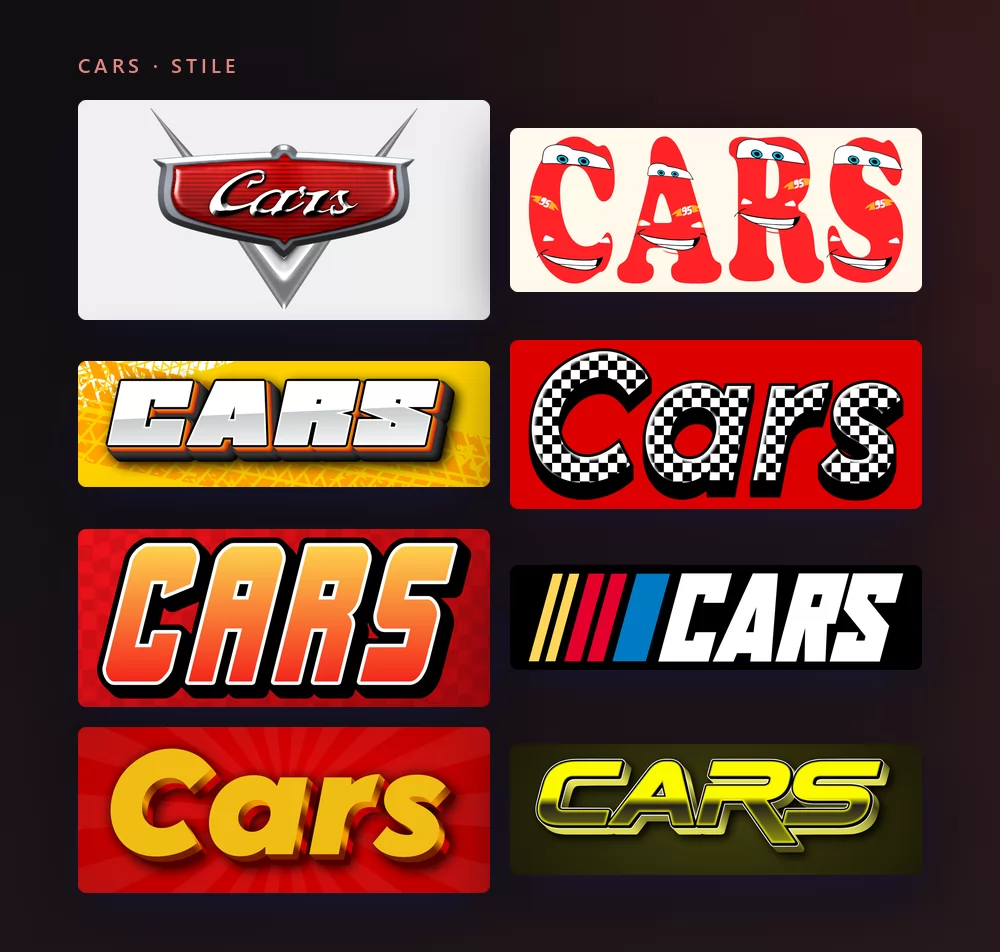
Alle stammen aus demselben Cars-Schriftgenerator, nur mit einem anderen Stil aus der Liste. Nichts zu installieren, kein Konto, und alle Stile oben sind kostenlos.
Über die Cars-Schrift
Cars ist ein Pixar-Film von 2006, eine Komödie in einer Welt, in der die Autos die Figuren sind. Sein Titel ist nicht getippt, er ist gebaut: eine Chromschrift in einem Wappenschild, näher am Ornament auf der Motorhaube einer Limousine der fünfziger Jahre als an einem Filmplakat.
Das Lettering selbst kommt Magneto Bold sehr nahe, gezeichnet von Leslie Cabarga und 1995 bei Font Bureau erschienen. Microsofts eigene Typografie-Seite beschreibt sie als Erinnerung an "die Chromleisten-Schriftzüge auf den runden Formen von Kühlschranktüren und Kofferraumdeckeln der vierziger und fünfziger Jahre", also genau die Epoche, die der Film zitiert.
Und hier ist, was jede Download-Seite auslässt. Magneto ist eine kommerzielle Schrift, und der übliche Rat lautet, sie zu kaufen. Aber Microsoft führt sie unter den Schriften, die es ausliefert, Datei Magnetob.ttf, und schreibt, dass sie in den Office-Anwendungen verfügbar ist. Wenn du Microsoft Office auf dem Rechner hast, hast du Magneto Bold sehr wahrscheinlich längst installiert.
Cars-Text erstellen
Schritt 1. Den Namen tippen
Öffne den Generator und ersetze den Beispieltext durch deinen. Das Emblem wird um das Wort herum gebaut, es ist also für einen Vornamen gemacht: das Schild füllt sich, während du tippst.
Schritt 2. Einen Stil wählen
Der Stil auf der Zielseite ist das Emblem: Chromschrift, roter Lack, silbernes Schild. In der Liste steht auch die ganze Rennseite des Films, Zielflaggen, Reifenspuren, Rennstreifen und die Buchstaben mit den Augen von Lightning McQueen. Im Reiter "Stil" lassen sich Füllung, Kontur und Schatten bei beiden ändern.
Schritt 3. Das Format wählen
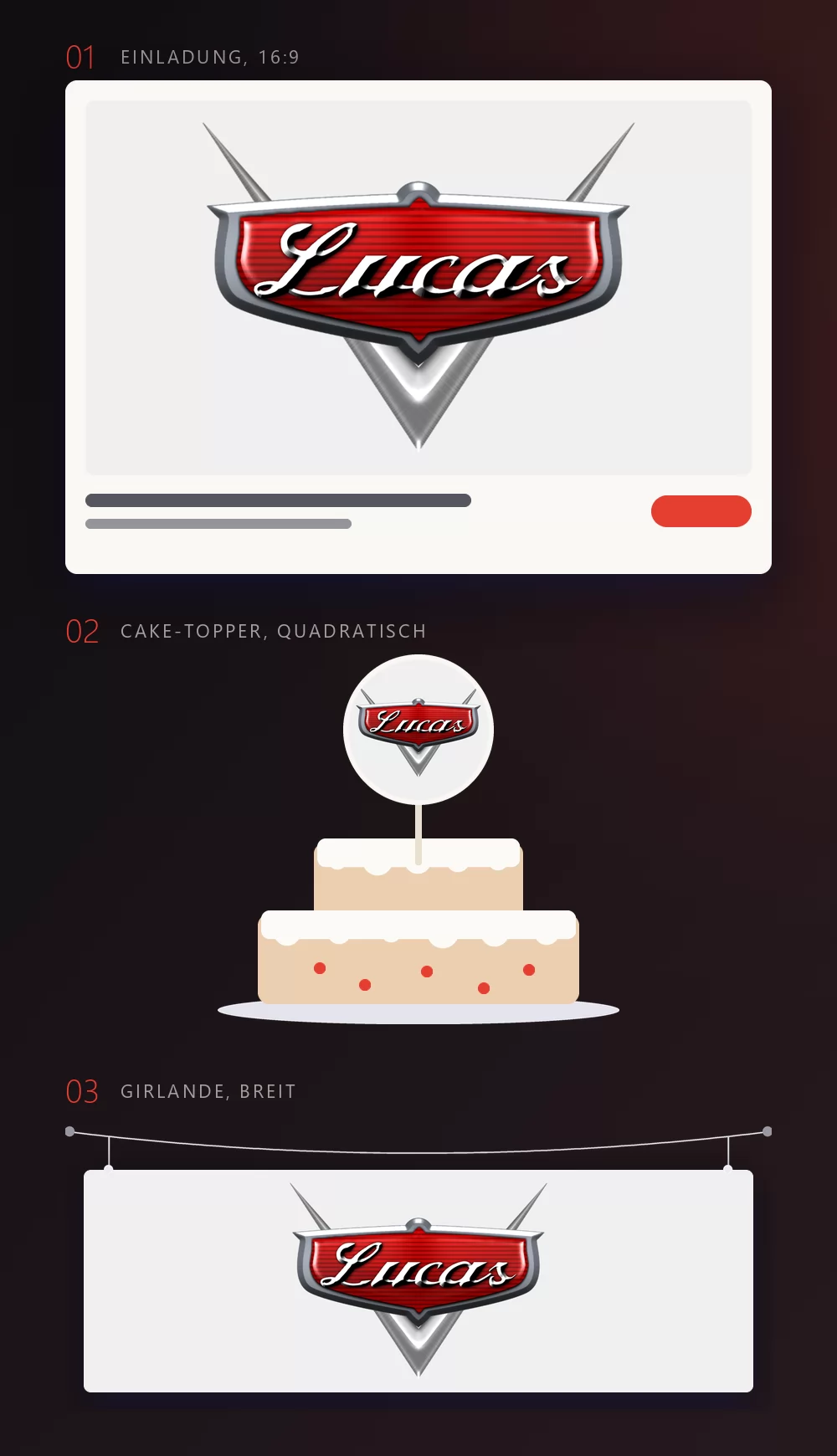
Lege das Format vor dem Export fest, dann wird hinterher nichts abgeschnitten. 16:9 für eine Einladung, quadratisch für einen Cake-Topper oder ein Profilbild, ein breiter Streifen für eine Girlande über dem Tisch. Die drei Anwendungen oben zeigen, was aus diesen Formaten wird, wenn sie an ihrem Platz sind.
Schritt 4. Herunterladen
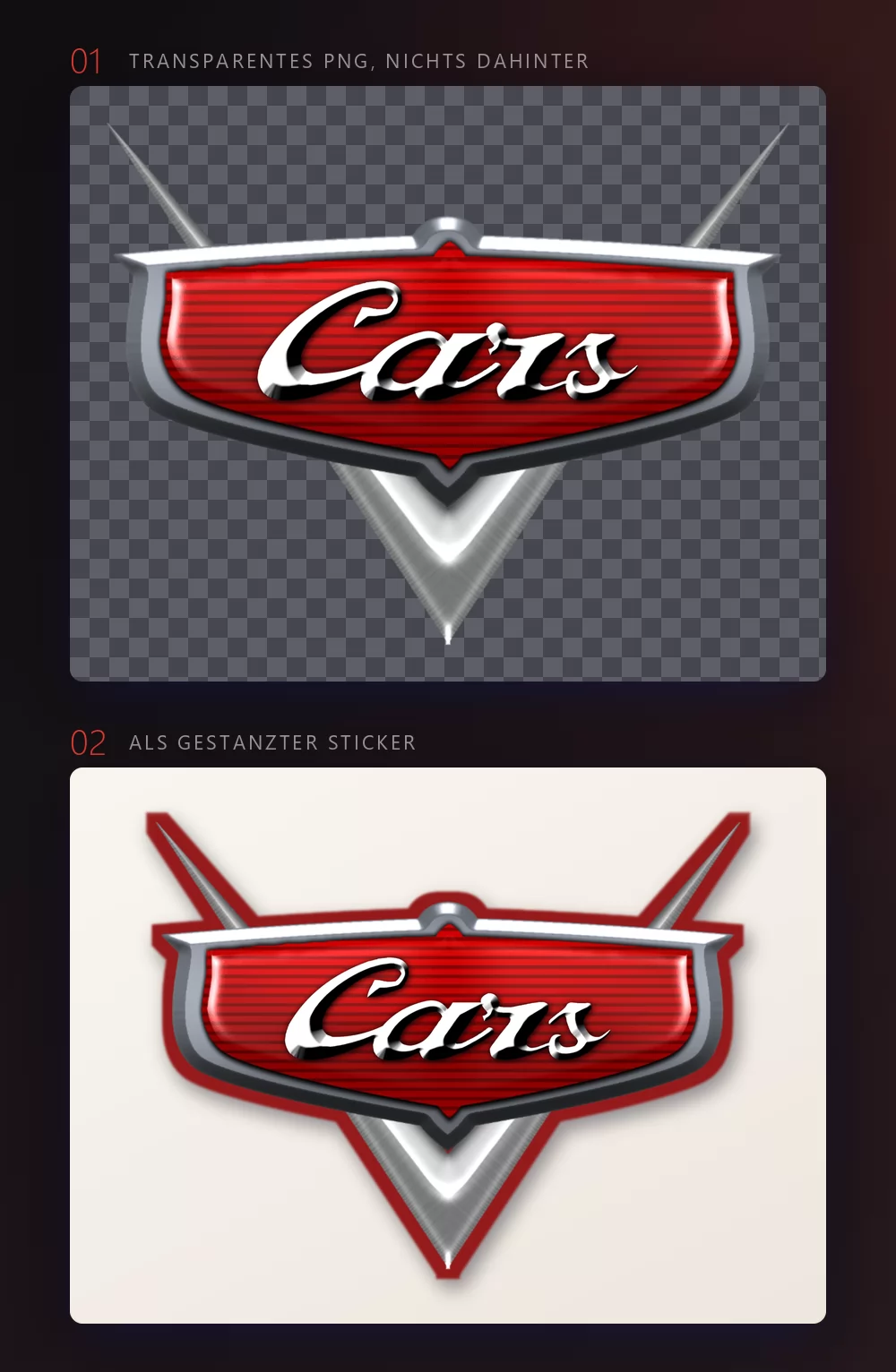
Nimm im Reiter "Download" das transparente PNG, wenn das Emblem auf etwas anderes soll: dein eigenes Foto, farbigen Karton, eine Folie, einen Schneideplotter. Diese Option übersehen die meisten, und für eine Feier ist sie die entscheidende, denn das Schild behält seine Form, statt in einem weißen Rechteck anzukommen.
Wie viele Buchstaben ins Emblem passen
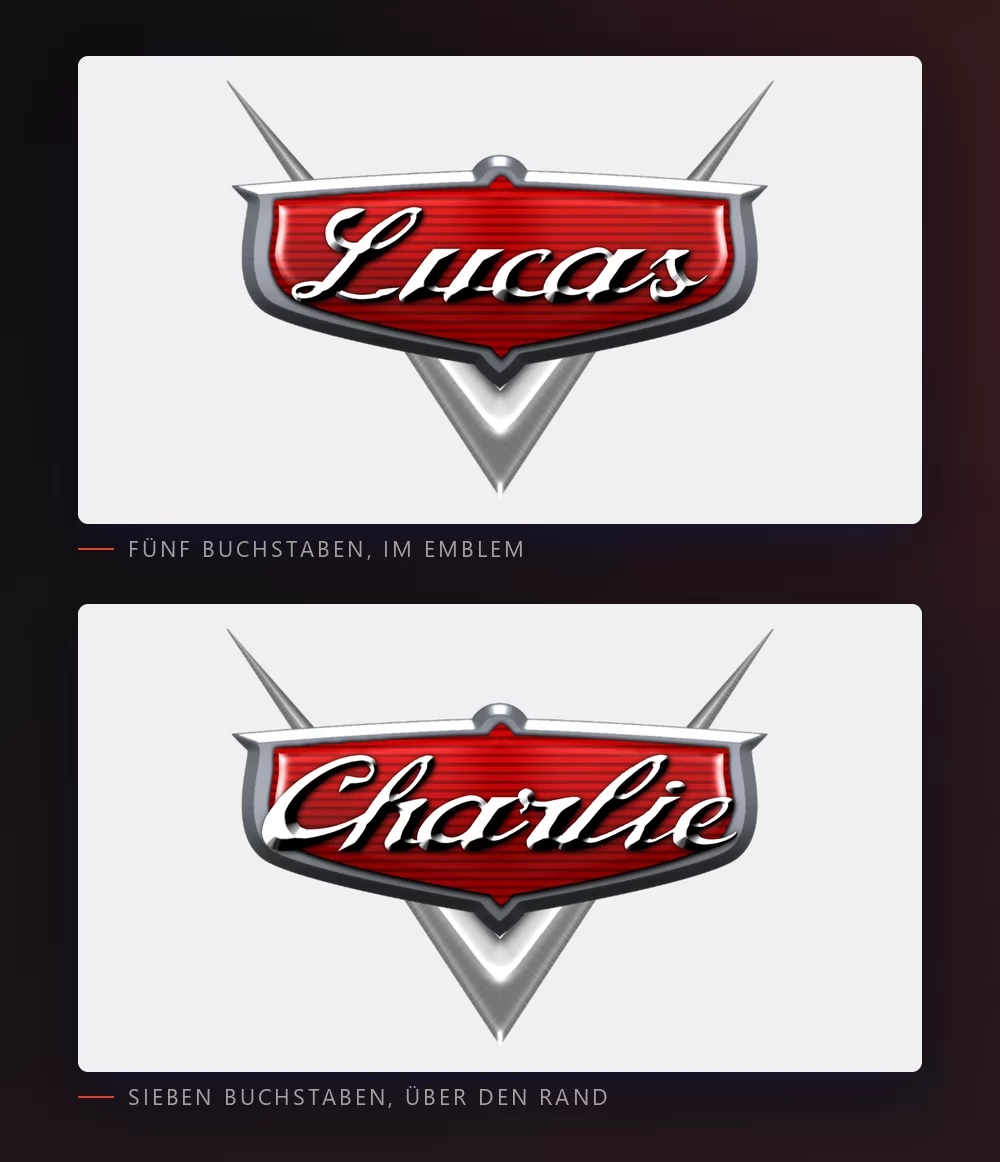
Wir haben es gemessen, denn davon hängt ab, welchen Stil du nehmen solltest. Das Schild fasst bequem fünf Buchstaben. Bei sechs berühren der erste und der letzte die silberne Kante. Bei sieben stehen sie draußen, wie oben.
Und anders als bei jedem anderen Stil hilft es nicht, den Text kleiner zu machen: das Emblem wächst mit dem Wort, das Verhältnis bleibt also gleich. Für einen längeren Namen ist die Antwort keine Einstellung, sondern ein anderer Stil. Die Rennversalien aus derselben Liste nehmen jede Länge, sie haben keinen Rahmen, aus dem sie fallen könnten.
Das Emblem oder die McQueen-Buchstaben
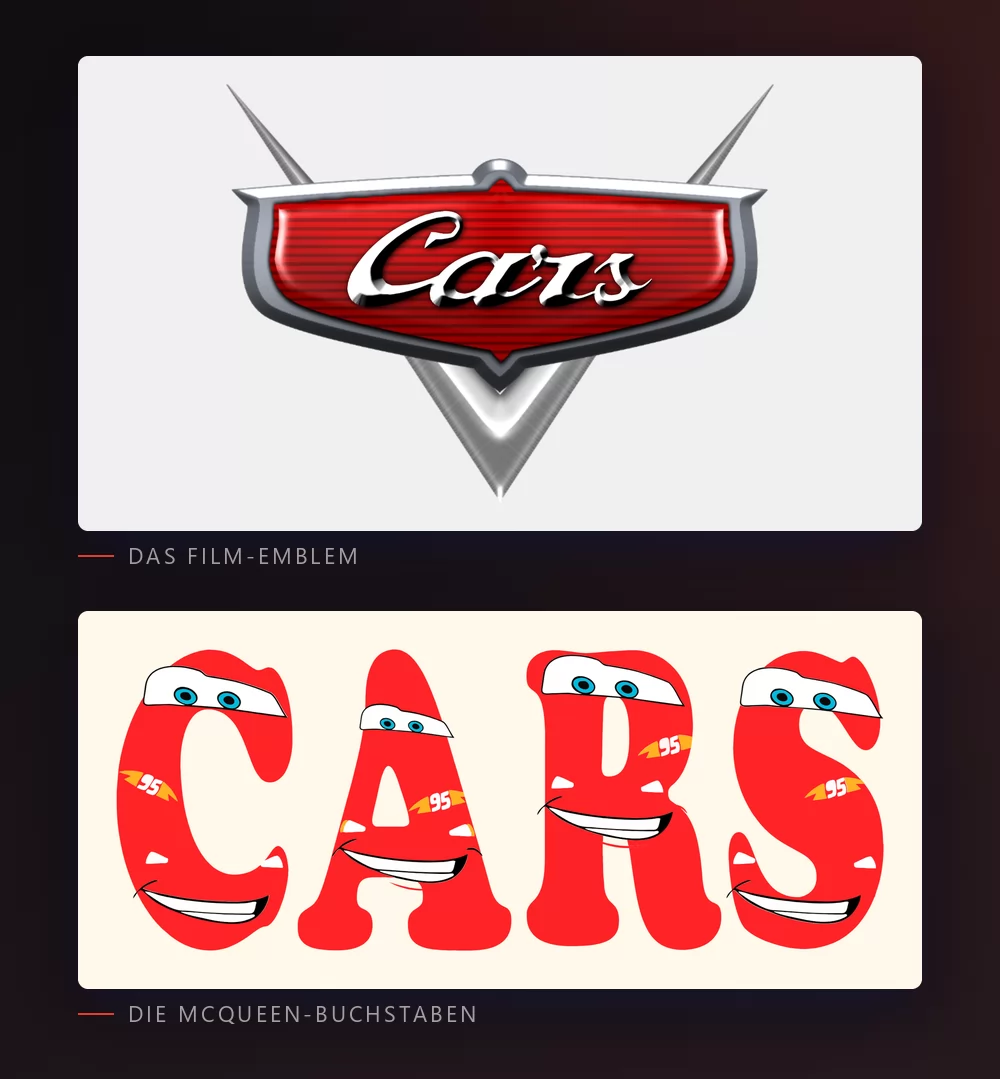
Das Emblem ist die Logoform des Films: die Chromschrift auf rotem Lack im silbernen Schild. Das ist es, was die Leute vor sich sehen, wenn sie "das Cars-Logo" sagen, und es ist das richtige für einen Namen auf einer Einladung.
Die McQueen-Buchstaben sind die andere Hälfte dessen, wonach gesucht wird: jeder Buchstabe ist ein kleines rotes Auto, mit den Augen in der Windschutzscheibe und dem 95er Blitz an der Seite. Sie sprechen von der Figur statt vom Film und wirken auf einer Girlande besser als auf ein Profilbild geschrumpft.
Beide stehen in derselben Liste: Du kannst einen Namen im einen ausprobieren und dann im anderen, ohne die Seite zu verlassen.
Welche Schrift installieren, wenn es denn eine sein soll
Magneto Bold ist die identifizierte Schrift, und der erste Ort, an dem du suchen solltest, ist dein eigener Rechner: sie kommt mit Microsoft Office. Öffne das Schriftmenü in Word und tippe den Namen. Steht sie da, ist die Sache erledigt, und du hast nichts gekauft.
Steht sie nicht da, wird Magneto von Font Bureau und seinen Händlern verkauft. Das ist eine echte kommerzielle Lizenz, die Kopien auf den Gratis-Schriftseiten sind also nicht legitim.
Für eine offene Lizenz ist die ehrliche Wahl Alfa Slab One auf Google Fonts, 2012 von JM Solé unter der SIL Open Font License gezeichnet. Sei dir klar darüber, was sie liefert und was nicht: sie ist eine Egyptienne, sie bringt also das Gewicht und die Bestimmtheit, nicht den Schwung. Sie ist die Schrift, die mehrere andere Generatoren stillschweigend verwenden.
Keine davon gibt dir das Schild. Das Emblem ist eine Form, keine Schrift, und deshalb zeichnet der Generator es um deinen Text herum, statt dich danach suchen zu lassen.
Wie mache ich eine Cars-Geburtstagsgirlande? Namen tippen, das breite Format wählen, das transparente PNG herunterladen und auf dem farbigen Papier drucken, das du verwendest.